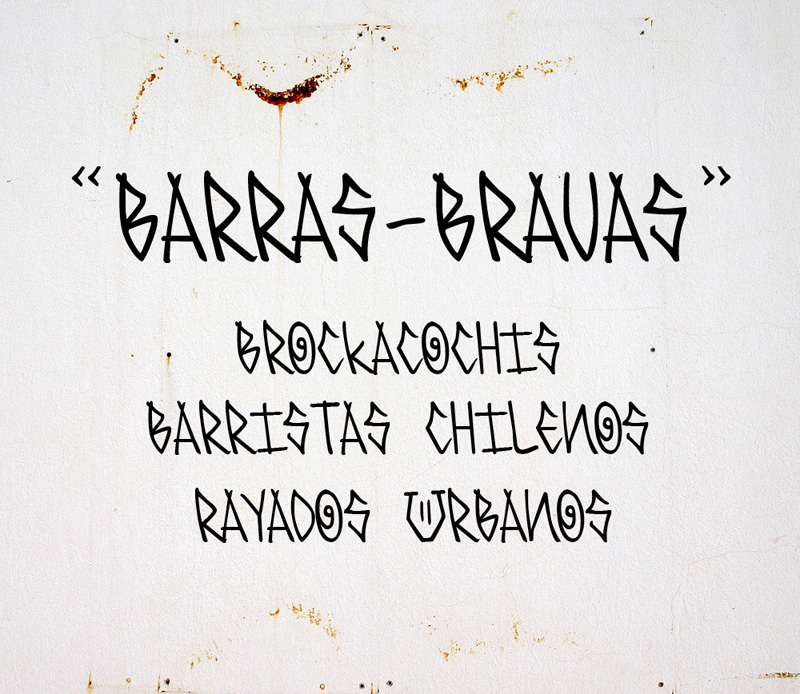
"BARRAS-BRAVAS" BASADO EN LA FORMA DE ESCRIBIR DE BARRISTAS CHILENOS EN LA CUAL , LA PUEDES ENCONTRAR EN CUALQUIER PARTE DE CHILE , YA SEA UN BAÑO PUBLICO , EN EL BUS , EN EL COLEGIO , ECT.. BASICAMENTE REPRESENTAR ALGO DE NOSOTROS ,QUE TIENE QUE VER CON NUESTRA SOCIEDAD Y NUNCA ES MOSTRADA. RODRIGO ARAYA SALAS RODRIGO_COMICS@HOTMAIL.COM |